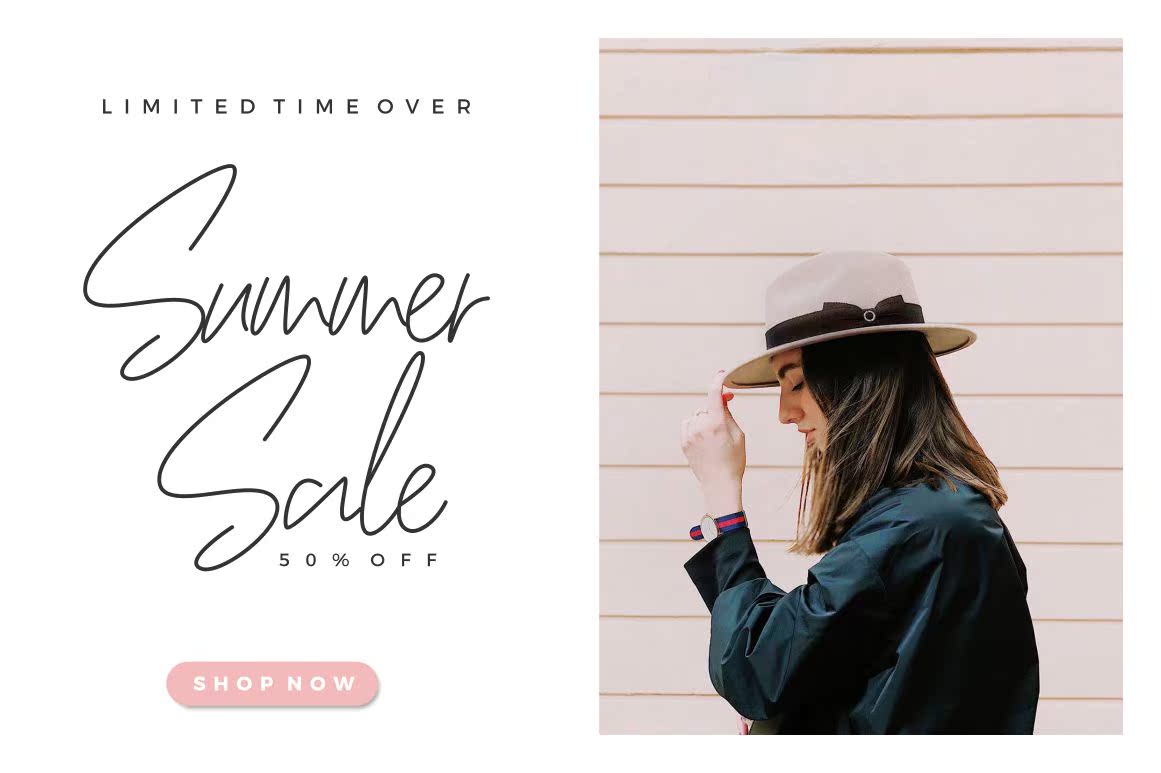
PrettyGirl是一款现代女性字体,每个字母都经过精心设计,使您的文本看起来更漂亮。采用现代的字体风格,这款字体将完善各种不同的项目:徽标、照片、水印、报价、博客标题、海报、婚礼、品牌、徽标、时尚、服装、信函、邀请函、文具等。PrettyGirl是一款现代女性字体,每个单独的字母都经过精心设计,使您的文字看起来美丽。使用现代的字体样式,此字体将完善任何不同的项目:徽标、照片、水印、报价、博客标题、海报、婚礼、品牌、徽标、时尚、服饰、信函、邀请函、文具等。